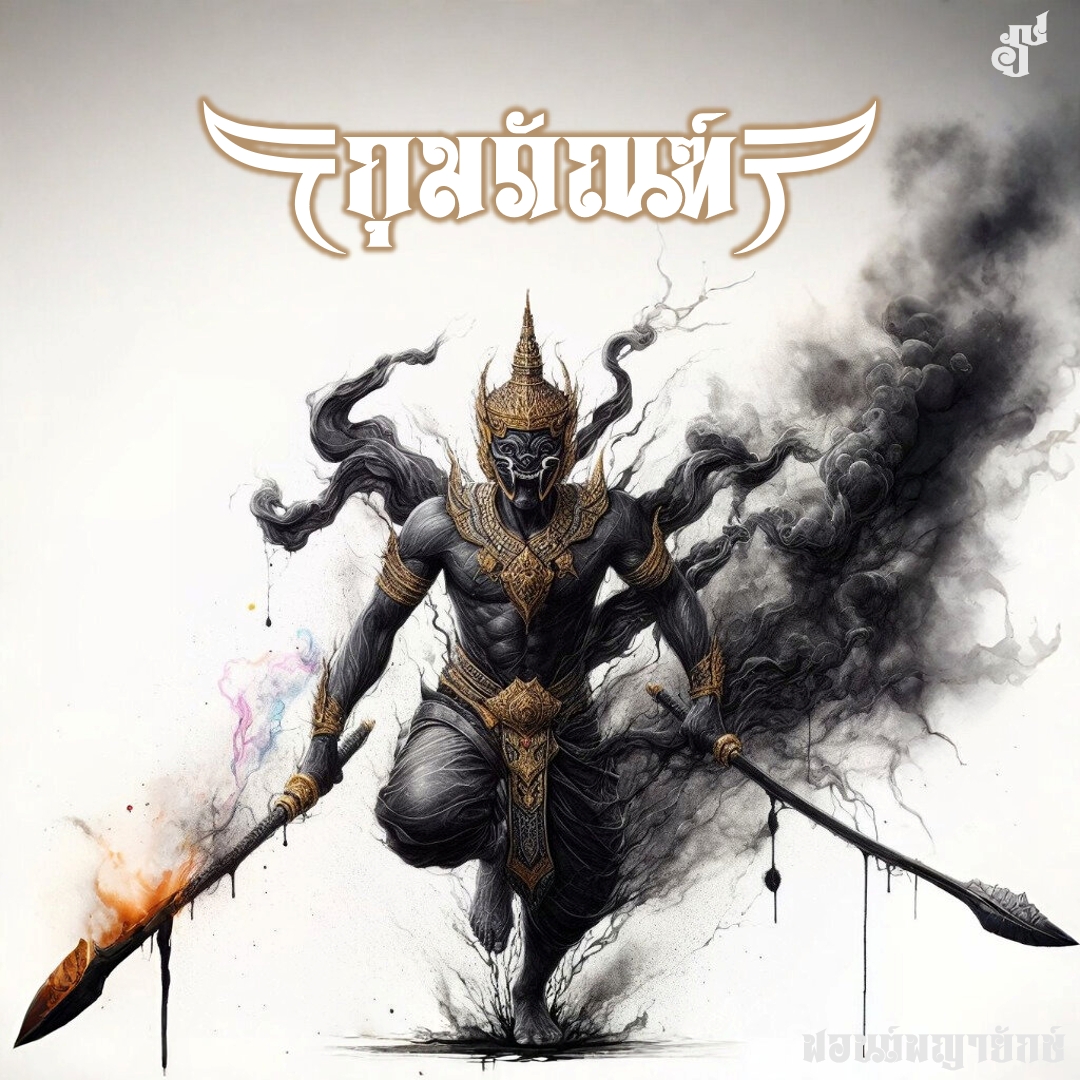
ฟอนต์ พญายักษ์
ฟอนต์พญายักษ์ แนวทางจากฟันบนยักษ์ไทย เติมเขี้ยวและกรอบปากด้วยวงเล็บ 3 แบบ "ฉณน" เป็นใหญ่เที่ยวไล่งับข้างบ้าน
ชื่อฟอนต์ : พญายักษ์
ฟอนต์พญายักษ์ แนวทางจากฟันบนยักษ์ไทย เติมเขี้ยวและกรอบปากด้วยวงเล็บ 3 แบบ "ฉณน" เป็นใหญ่เที่ยวไล่งับข้างบ้าน